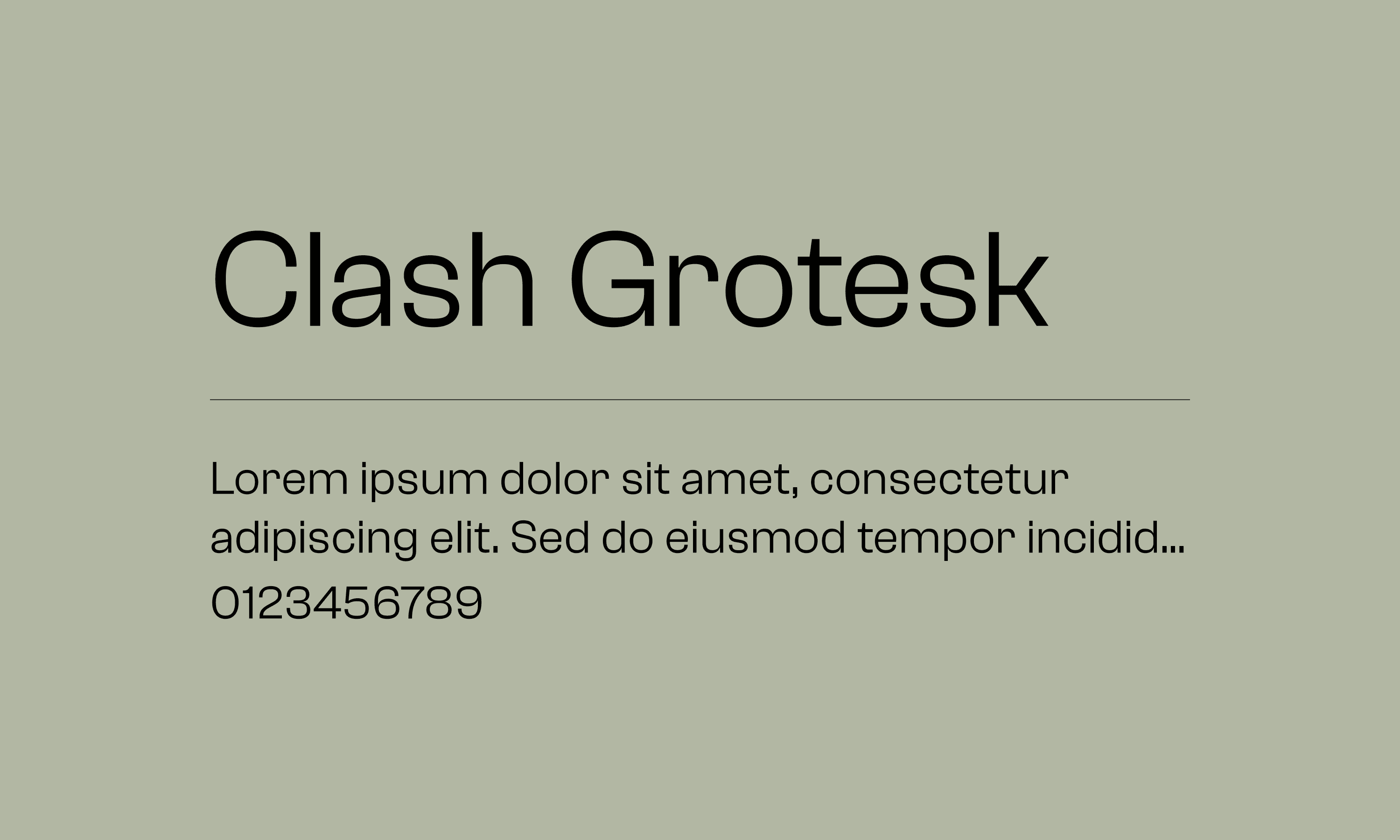
Clash Grotesk
Clash Grotesk 是一款带有独特设计的无衬线字体家族。尽管该家族的六种样式整体属于新哥特风格,但有一个特点让它与同类字体有所不同:其字母形态具有非常小的“开口”。这些开口位于字母内空的边缘,例如字母“c”的右侧两端之间的空间非常小,看起来几乎要闭合。Clash Grotesk 引人注目,但这种“设计技巧”并不过分。它足够温和,可以用于企业形象设计,同时又充满活力,适合编辑设计使用。